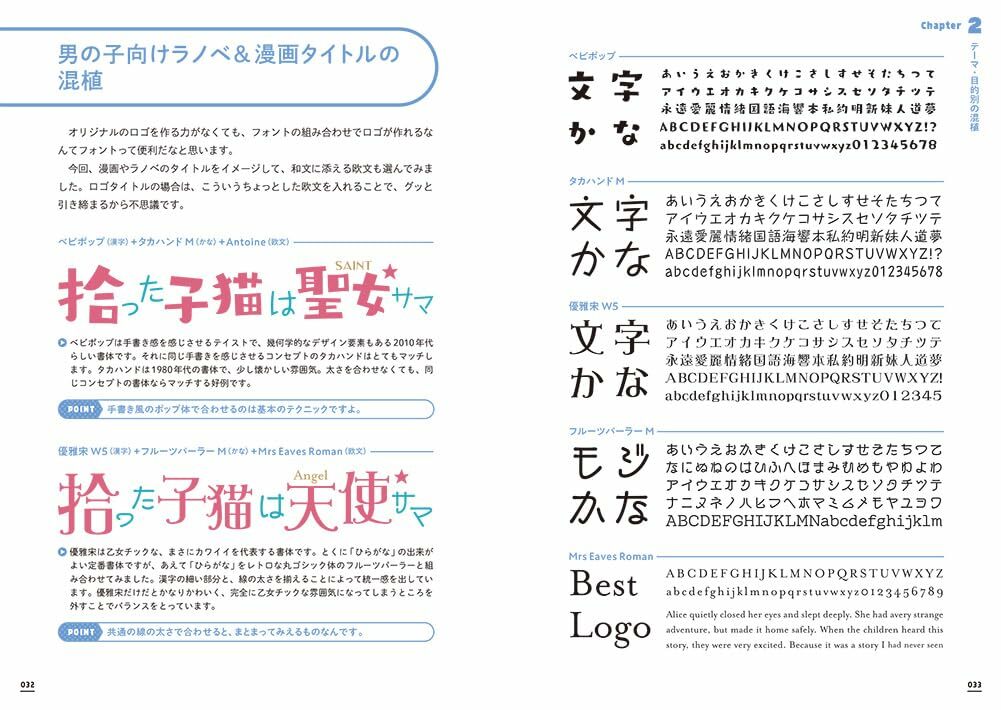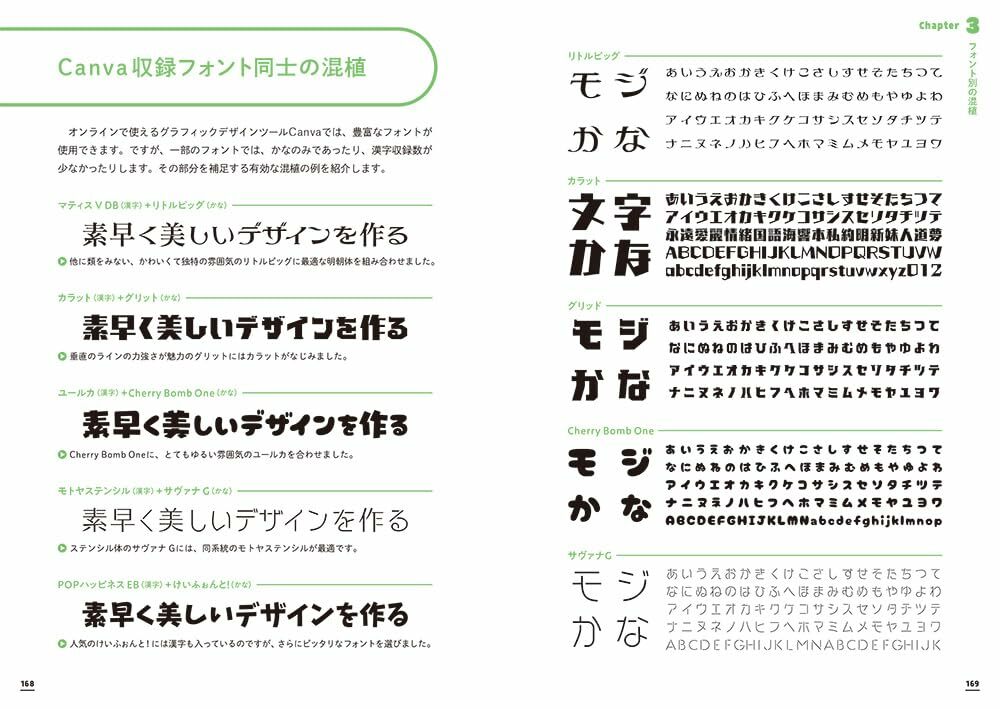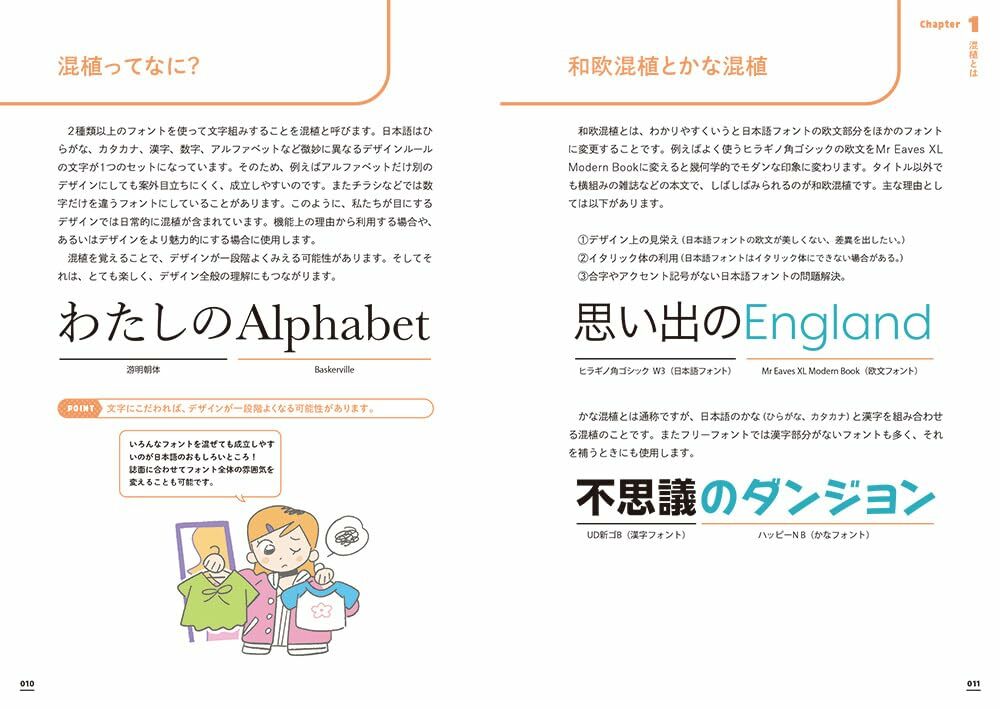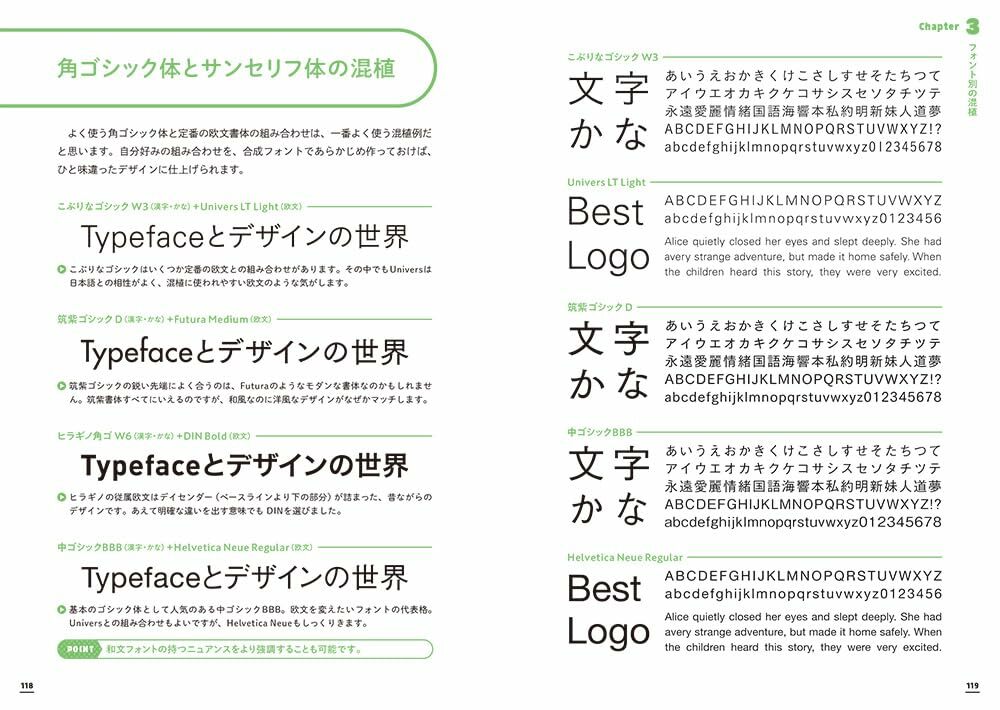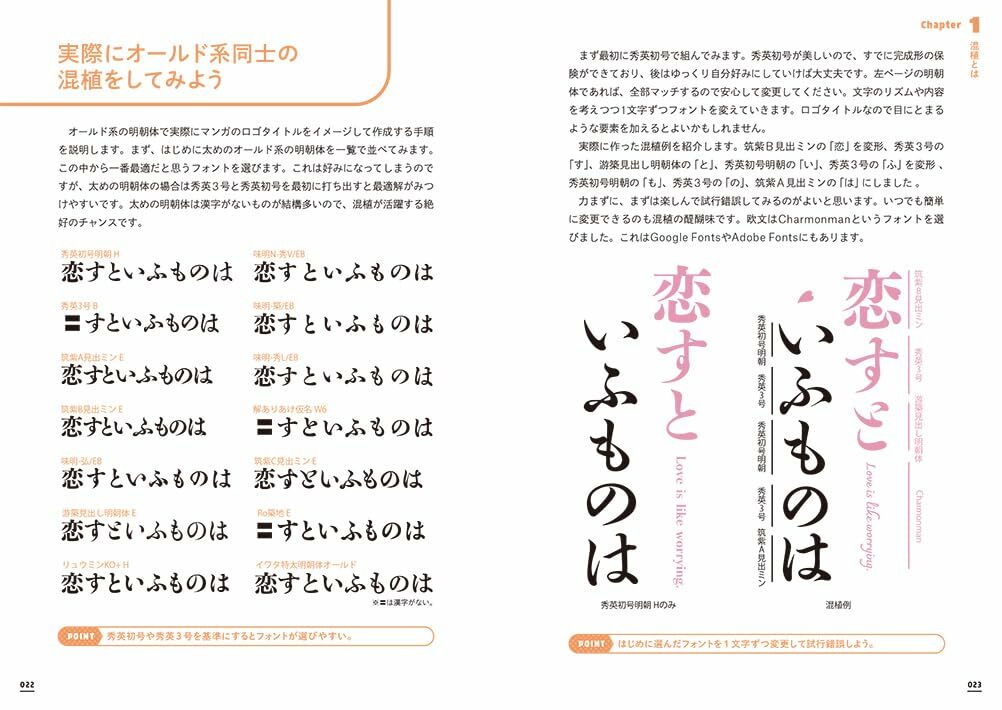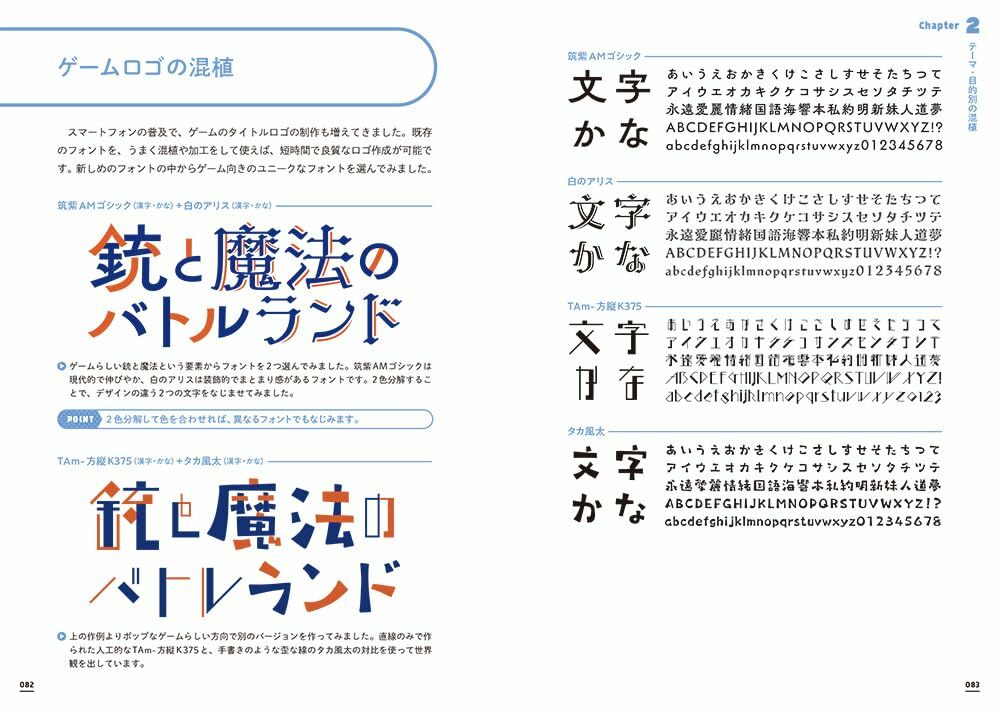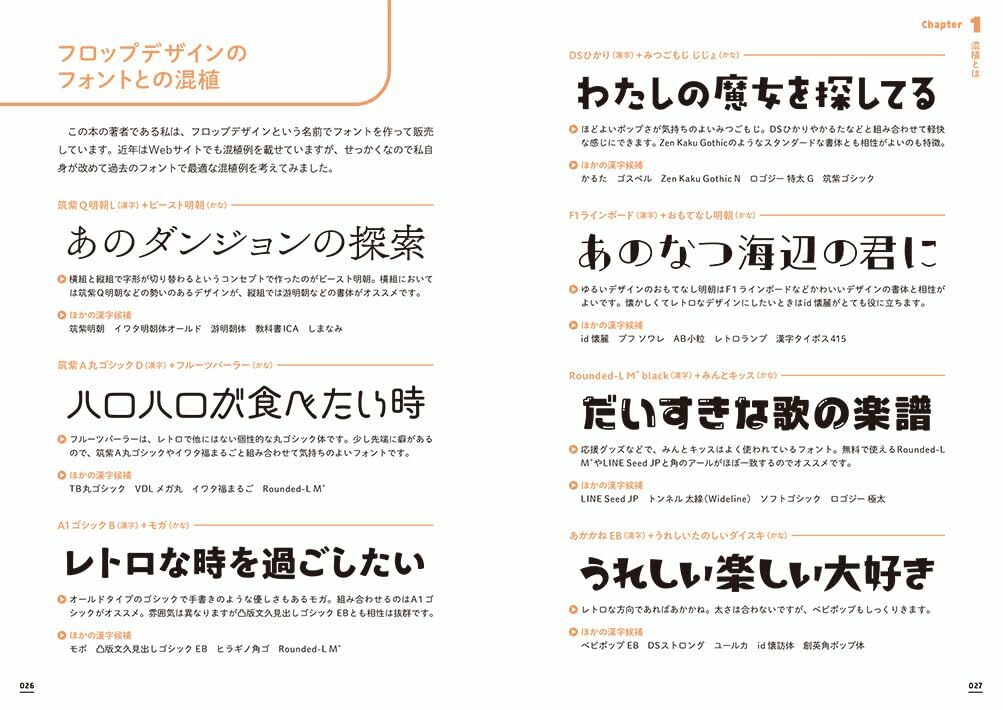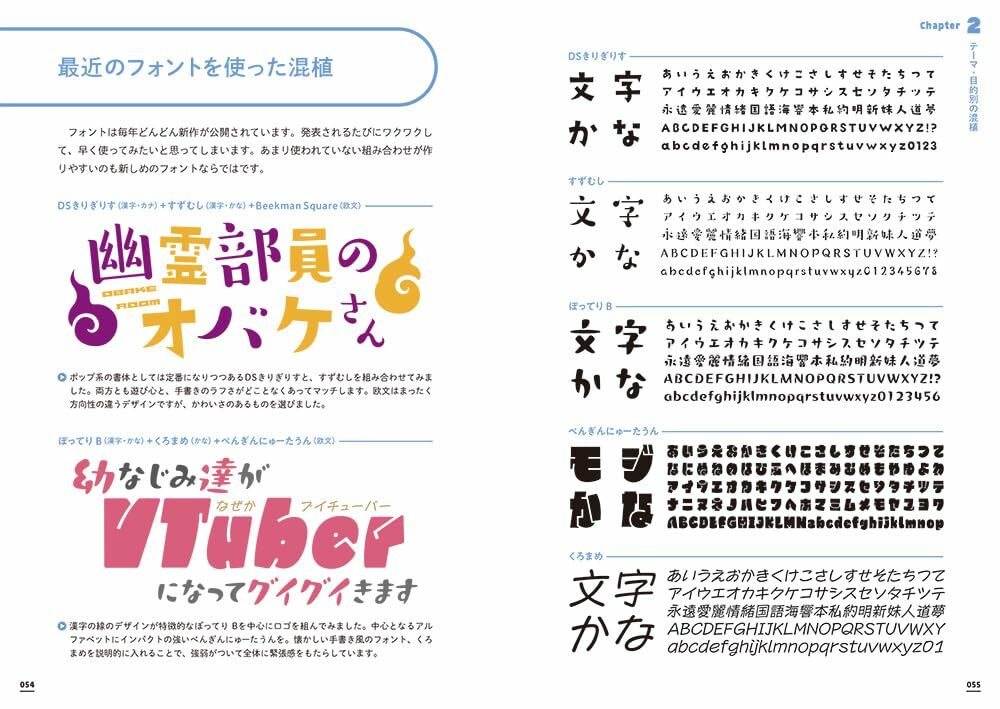
混植の本 フォントのカップリングガイド
作者     フロップデザイン (著)
【書籍簡介】
《從字體廠商到免費字型,混合排版一次大公開!》
使用兩種以上的字型進行排版設計,稱為「混植」。
本書收錄了從使用設計字型進行華麗混植的例子,到為了讓正文更為和諧、取代附屬英文的實用混植範例。左頁展示了混植範例,右頁則是介紹範例中使用的字型組合。
這本書能夠解決你在標題設計上的煩惱,並幫助你更有效地運用現有字型資源!
〈推薦給這些讀者〉
喜歡字型的朋友
買了字型卻不知道怎麼使用的朋友
有 Adobe 授權,對字體有興趣但不熟悉合成字型的朋友
主要從事排版設計或標誌設計的設計師
〈本書內容〉
■CHAPTER 1 什麼是混植?
■CHAPTER 2 依主題和目的進行混植
■CHAPTER 3 依字型進行混植
■CHAPTER 4 設計師推薦的最佳字型搭配
〈CHAPTER 4 設計師推薦的最佳字型搭配〉 AYA graphics/Anseek Design/甲斐史友也/加納佑輔/小林功二/Typingart & Co. 字體鐵道/玉野葉月/的場仁利 Mat N.
〈本書特色〉
這是一本專門討論混植排版的書!
從標誌設計的混植到正文排版的混植,字型包含從字體廠商到免費字型等各種類型!